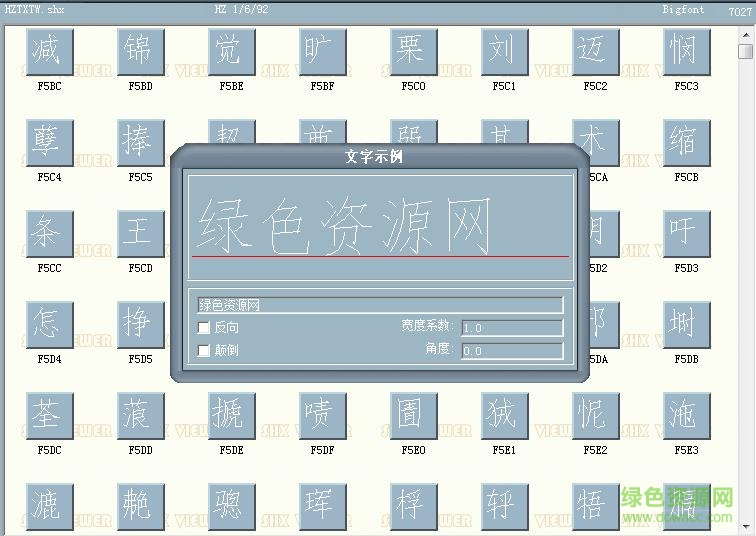
hztxtw.shx字體的形式擁有自己獨(dú)特的字體結(jié)構(gòu),除了在cad軟件中實(shí)現(xiàn)制圖作用之外,還能夠運(yùn)用到眾多的媒體行業(yè)進(jìn)行藝術(shù)字創(chuàng)作等,擁有廣泛用途,快來(lái)綠色資源網(wǎng)下載吧!
在使用中常常帶來(lái)很不錯(cuò)的直觀(guān)視覺(jué)欣賞,這款字體的優(yōu)美之處在于能夠讓人感受到柔美的字體線(xiàn)條樣式,讓你在使用與看圖中都獲得最佳視覺(jué)與精神的體驗(yàn)!
1、在眾多的cad字體中擁有大量的形文件,讓你能夠不斷的完成各類(lèi)圖形圖像的圖紙制作
2、cad字體能夠帶給用戶(hù)不錯(cuò)的使用體驗(yàn),輕松的獲得最佳的字體樣式